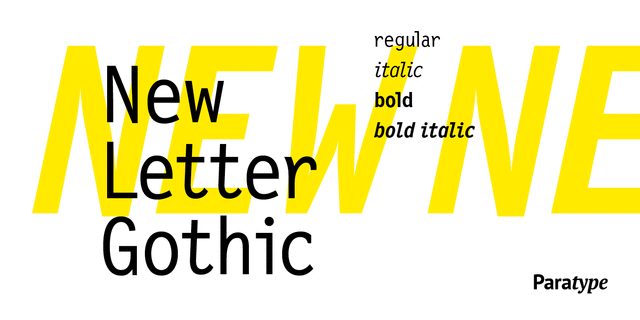
ПТ Нью Леттер Готик Гарнитура разработана для фирмы ParaType в 1999 году (дизайнер Гаянэ Багдасарян) на основе моноширинного шрифта Letter Gothic 12 Pitch (дизайнер Роджер Робертсон, 1956-62). Поскольку благодаря ясной и легкочитаемой форме своих знаков шрифт Леттер Готик весьма популярен сейчас для набора акцидентной и рекламной продукции, возникла идея создать на его основе шрифт с пропорциональными ширинами букв, сохраняя особенности их рисунка. Предназначен как для акцидентного, так и для текстового набора. Шрифт Нью Леттер Готик награжден дипломом «За совершенство в дизайне шрифта» на Московском международном конкурсе шрифтового дизайна «Кириллица’99»